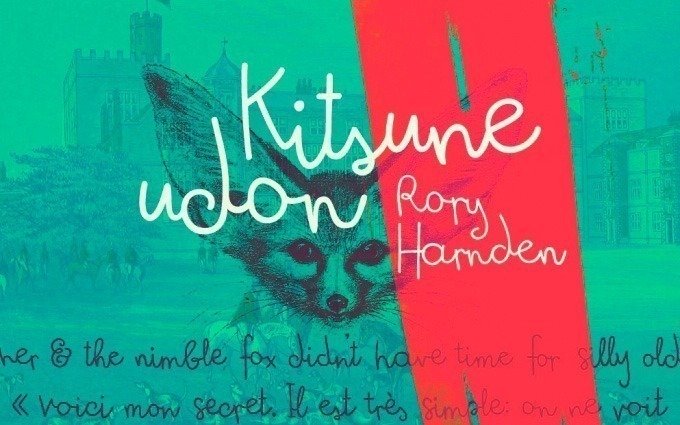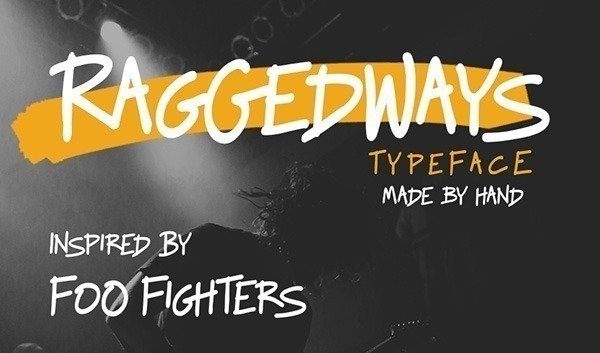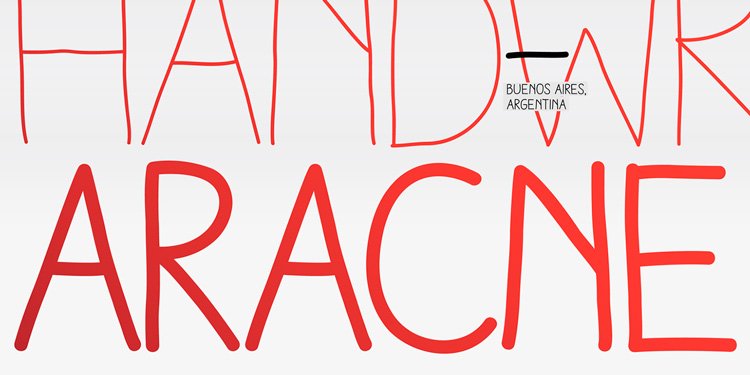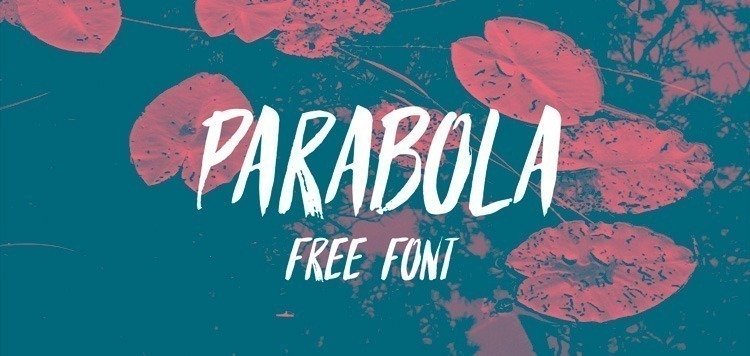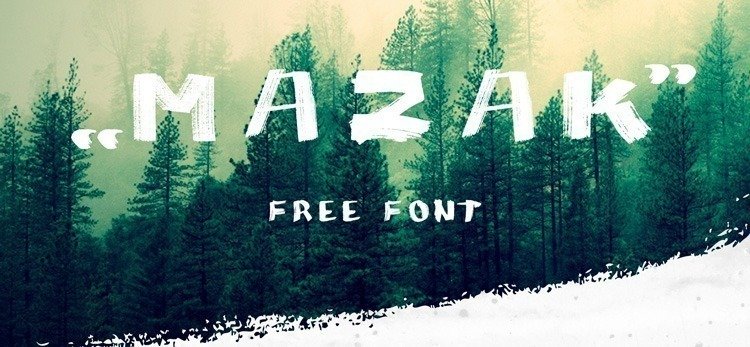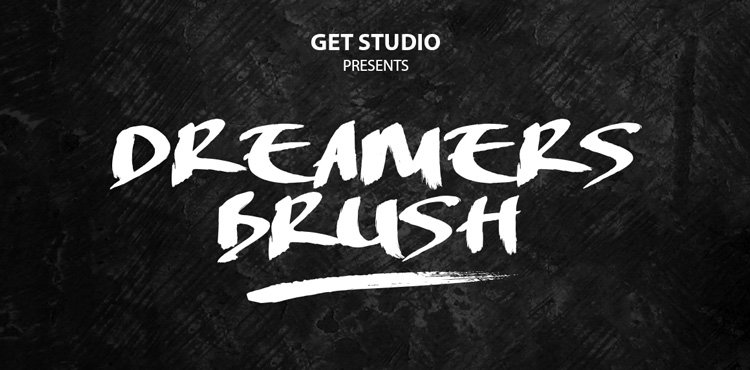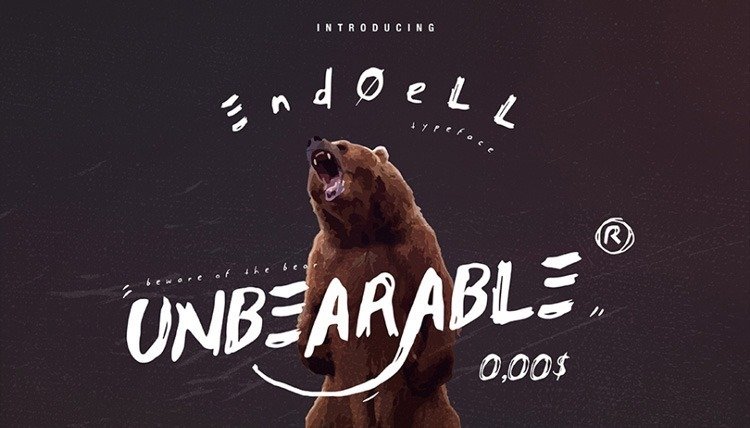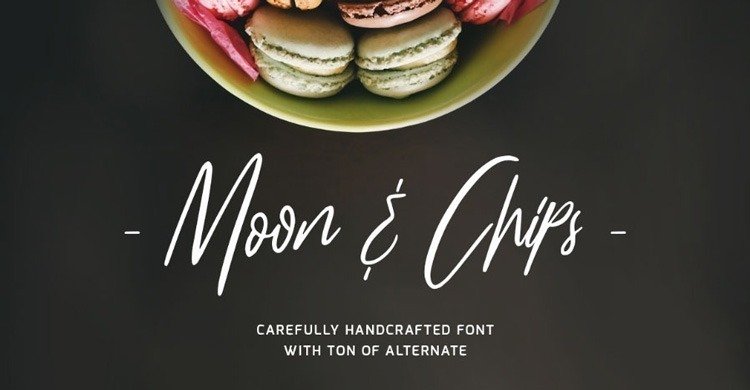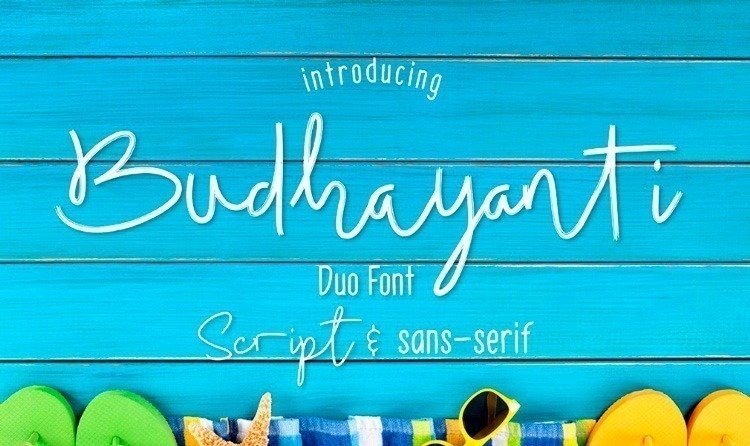
22 fontes com efeito “escrito à mão”
Fontes com efeito “escrito à mão”, ou manuscrito, é procurado por muitos profissionais criativos que querem dar um toque especial em seus projetos.
Convites de casamento, cartazes, pôsteres e flyers são apenas alguns exemplos de aplicação de fontes desse tipo.
Agora sim, fique com as fontes com efeito manuscrito:
Summer Hearts
Bodega Script
Kitsune Udon
Raggedways
Fabu
Black Top
Markfreer
Aracne
Italo
Parabola
Mazak
Dreamers Brush
Unbearable
Moon & Chips
Mr. Accordion
Triovcle
Marziona
Budhayanti
The Conquer
The Cursive Script
FFF Tusj
Good Vibes